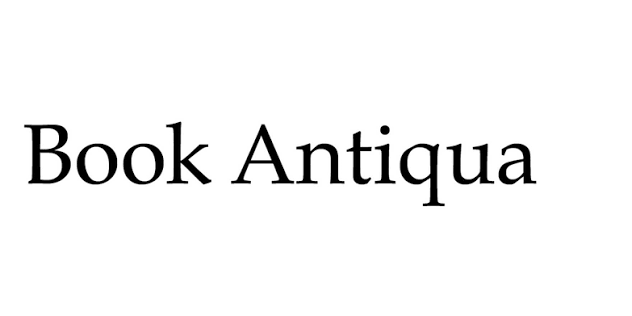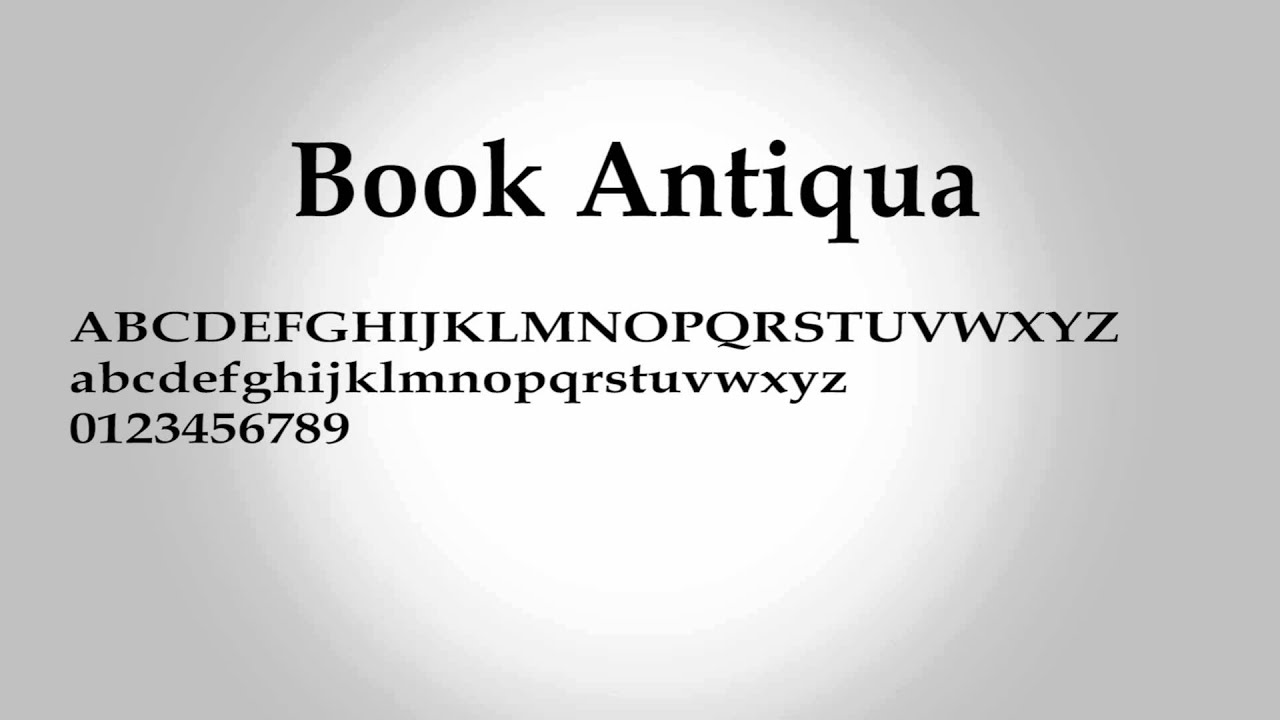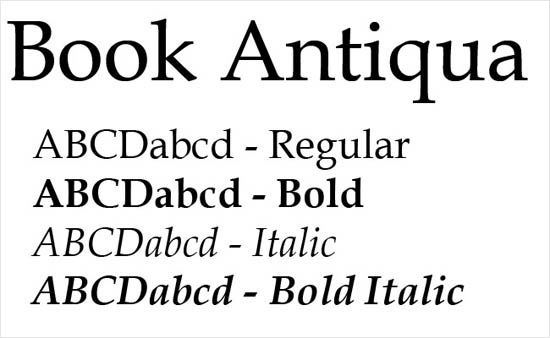
Font Book Antiqua Việt hóa là bộ phông chữ có chân (Serif) chuyển tiếp kinh điển, nổi tiếng với vẻ đẹp trang trọng, cổ điển và cực kỳ tối ưu cho việc đọc các khối văn bản dài. Được phát triển như một phần trong hệ sinh thái phông chữ của Microsoft, Book Antiqua mang phong cách thanh lịch, ấm áp, gợi nhắc đến nghệ thuật in ấn sách báo truyền thống châu Âu. Doozypack.vn cung cấp link tải trọn bộ chuẩn kỹ thuật, giúp bạn sở hữu phông chữ đẳng cấp này, hỗ trợ đầy đủ tiếng Việt không lỗi dấu để tự tin thiết kế bao bì, nhãn mác và bộ nhận diện thương hiệu chuyên nghiệp.
Đặc điểm thẩm mỹ độc đáo của bộ font Book Antiqua
Book Antiqua không đi theo sự sắc nhọn lạnh lùng của các phông chữ hiện đại; nó mang đến một ngôn ngữ thị giác đầy tính học thuật, uy tín và mang lại cảm giác vô cùng tin cậy cho người xem.
Phong cách Transitional Serif lấy cảm hứng từ nghệ thuật in sách cổ điển
Đặc trưng lớn nhất của Font Book Antiqua Việt hóa là cấu trúc chân chữ (serif) có độ dày dặn vừa phải, các đường nét chuyển tiếp mượt mà lấy cảm hứng từ các bản in Phục hưng. Thân chữ có tỷ lệ cân đối, tạo nên một nhịp điệu Typography vô cùng ngăn nắp, trang nghiêm. Khi đặt Book Antiqua làm tiêu đề hoặc nội dung trên bao bì, sản phẩm của bạn sẽ ngay lập tức toát lên vẻ ngoài lâu đời, uy tín và chuẩn mực.
Cấu trúc chữ rộng rãi và độ dễ đọc vượt trội
Các ký tự của Font VNBook Antiqua sở hữu khoảng hở trong chữ (counter) rộng rãi và x-height lớn. Thiết kế này giúp phông chữ duy trì độ dễ đọc (legibility) xuất sắc ngay cả khi in ở kích thước siêu nhỏ trên tem nhãn hoặc tài liệu hướng dẫn sử dụng kèm theo trong hộp sản phẩm, giúp người tiêu dùng dễ dàng tiếp nhận thông tin.
Ưu điểm nổi bật của bản Font Book Antiqua Việt hóa
Khi ứng dụng các phông chữ kinh điển vào thị trường trong nước, sự chỉn chu về dấu câu là yếu tố quyết định đến tính chuyên nghiệp của ấn phẩm:
- Khắc phục triệt để lỗi dấu tiếng Việt: Phiên bản Việt hóa đã được đội ngũ thiết kế trau chuốt thủ công từng dấu câu. Các dấu sắc, huyền, hỏi, ngã, nặng được vẽ với tỷ lệ cân đối, đặt ở vị trí thoáng đãng so với thân chữ, không gây cảm giác chắp vá hay đè nét làm mất tính thẩm mỹ.